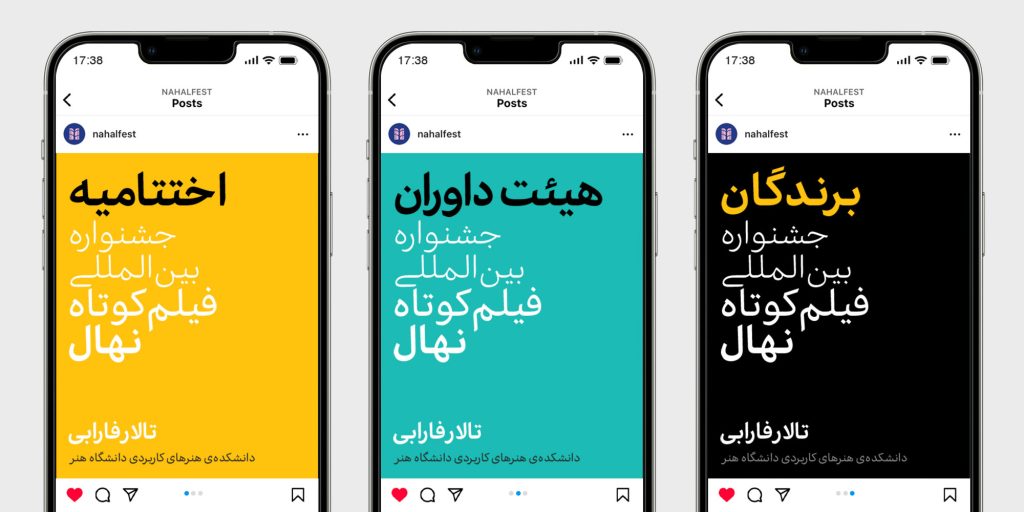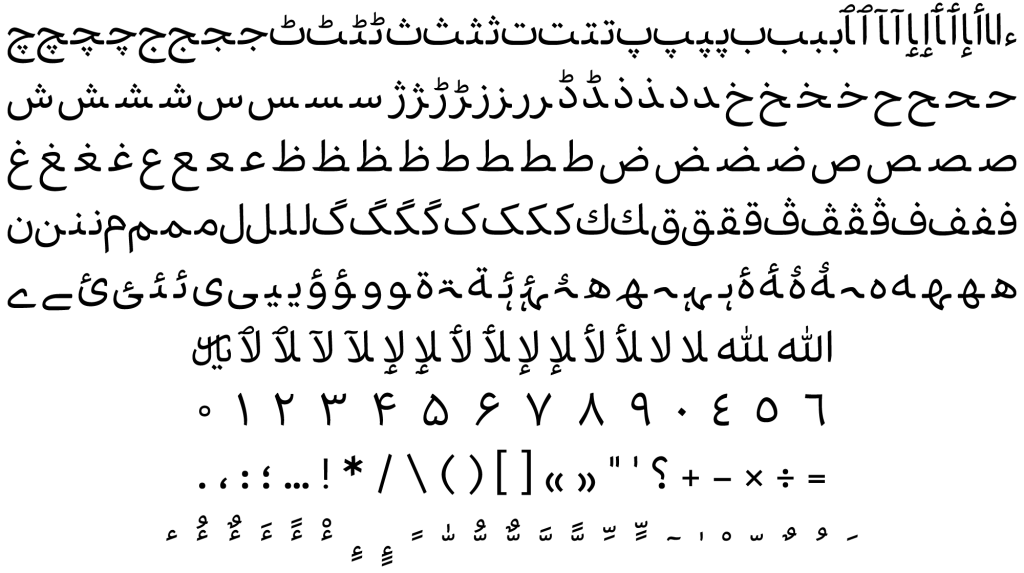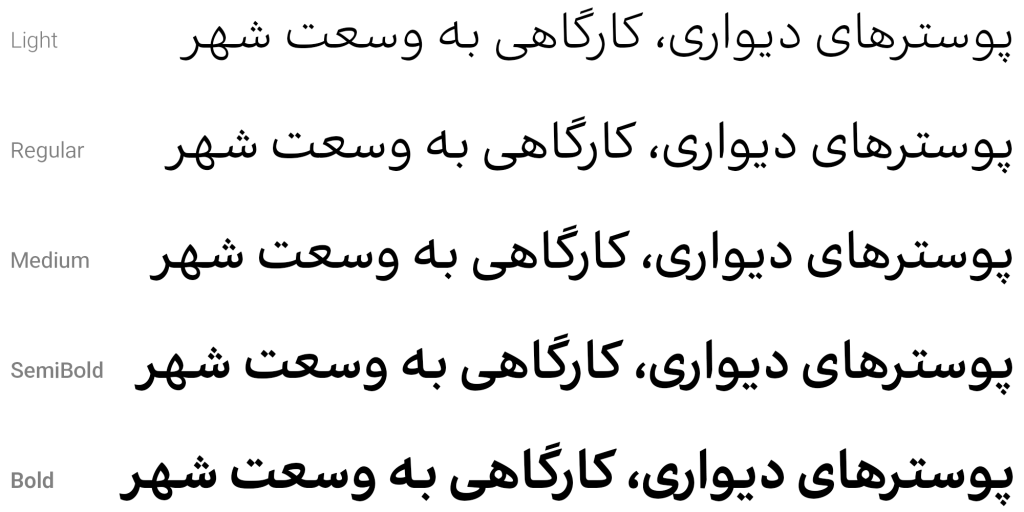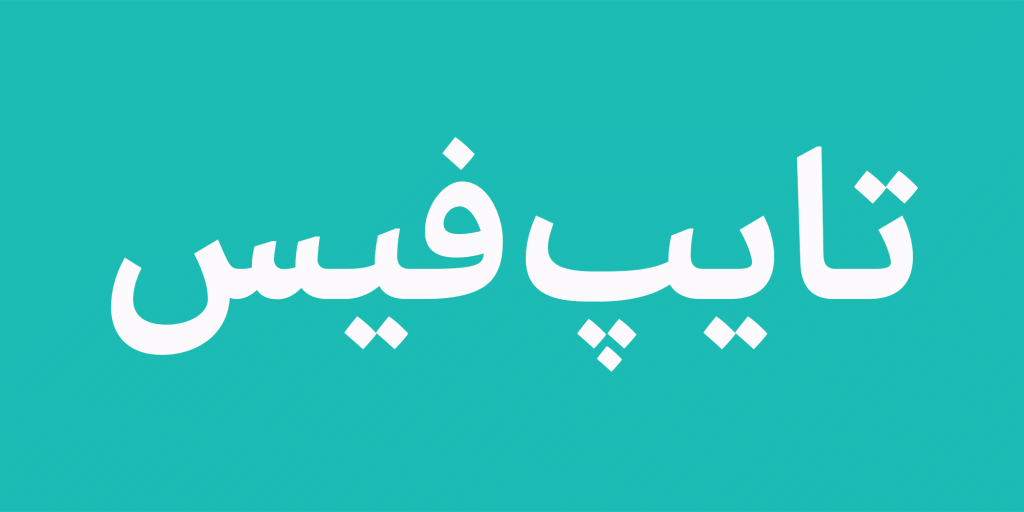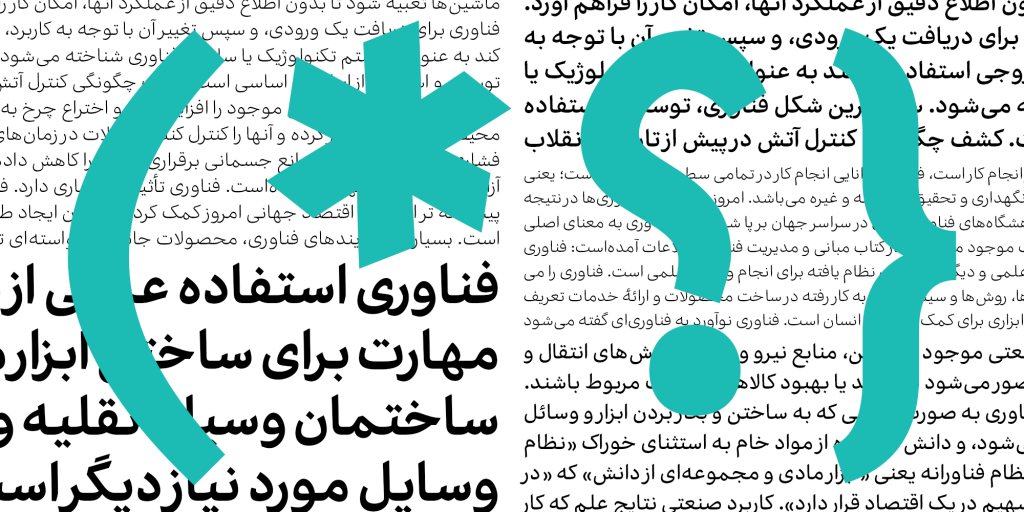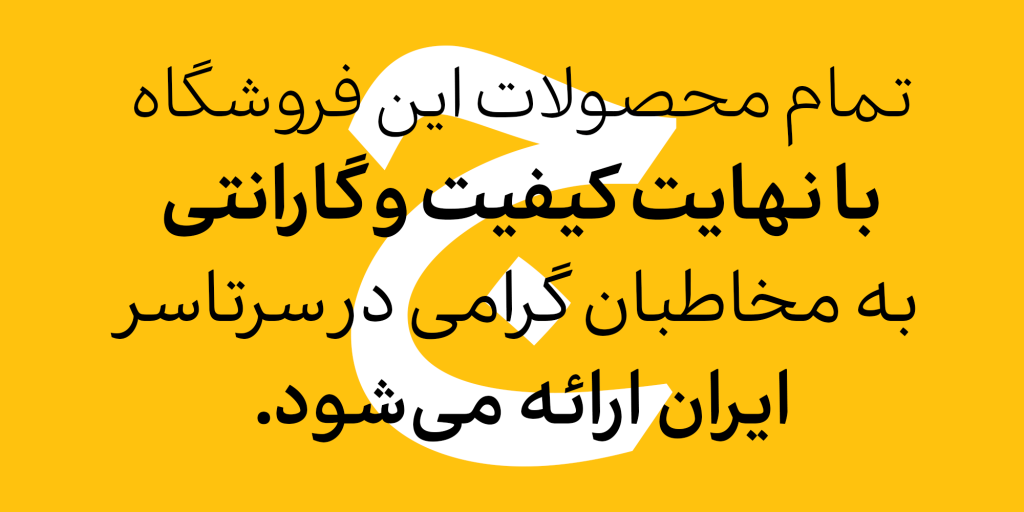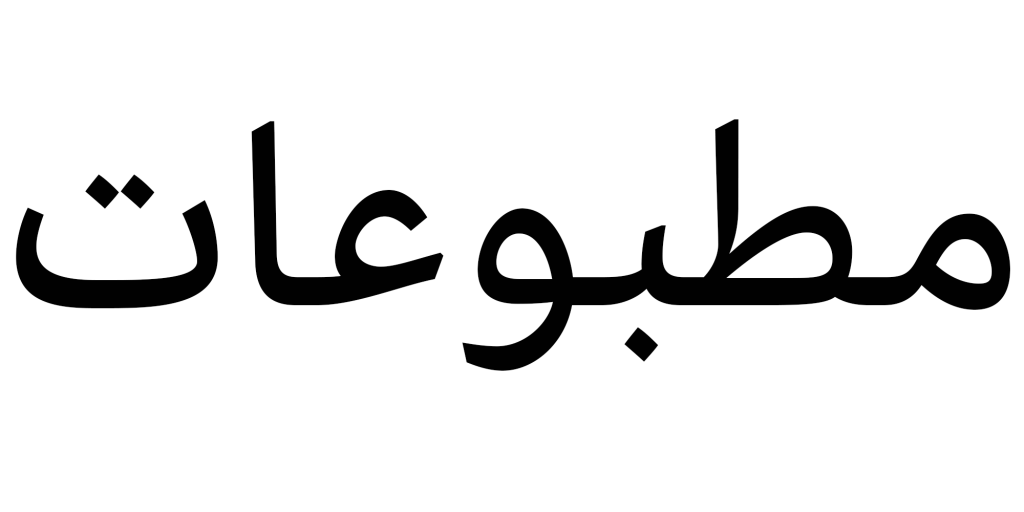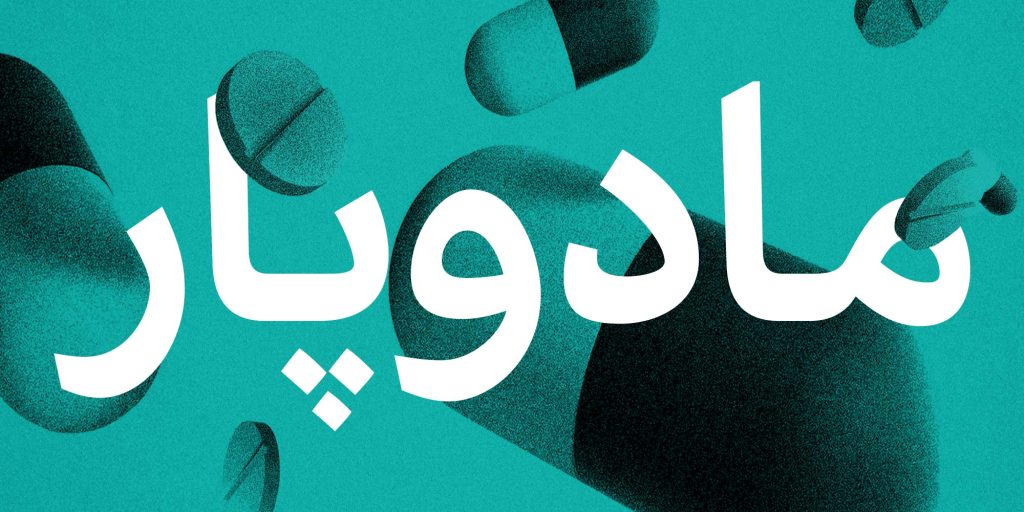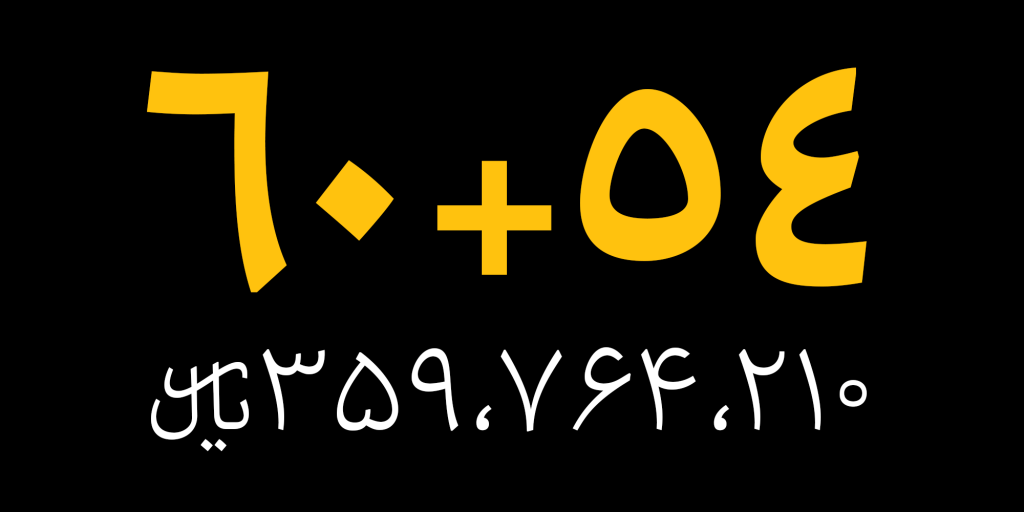
فونت اکران قلمی مناسب فضای وب و دیجیتال
فونت اکران تایپ فیسی که توسط طراحان آن رضا غفاری و بهمن اسلامی ابداع گردیده .این تایپ فیس اساسا ساخته شده برای محیط های دیجیتال و فضاهای وب و شبکه های اجتماعی است به سبب داشتن مهم ترین ویژگی این قلم که خوانایی آن است. فونت نورا هم به مانند این تایپ فیس کاربری خود را در فضاهای گفته شده دارد . دقیق و ظریف است و ظرافت بی نظیری را در طراحی فرم های حروف خود داشته است.
پیش تر نیز گفته شد که اکران اساسا ساخته شده برای دنیای دیجیتال می باشد در هر نوع اپلیکشین و فضای وب سازگار است و خوانایی خود را حفظ می کند. می توانید طراحی های خود را با استفاده از این تایپ فیس در نرم افزار های مربوطه از جمله آدوبی فتوشاپ، ایلسترتور و اینشات و … انجام دهید .
در نسخه های جدید تر آن گستردگی کاربرد آن فراتر رفته و برای محیط های اپلیکیشن های بازی و گیم در موبایل و … مورد استفاده قرار می گیرد. این تایپ فیس با بهره بردن از خطوط براق و منحنیهای دقیق و ظریف
خود، هر متنی را زیبا و جذابتر مینماید. این قلم زیبا مناسب برای متون طولانی با هر اندازه ریز و کوچک می باشد و نسخه بازسازی شدهٔ فونت تجرید است که سعی بر افزایش میزان زیبایی و خوانایی آن نسبت به تجرید گردیده است.
در زیر تصاویری نمونه از این قلم با ظرفت های دقیق و منظم آن برای شما دوستان آماده گردیده است.